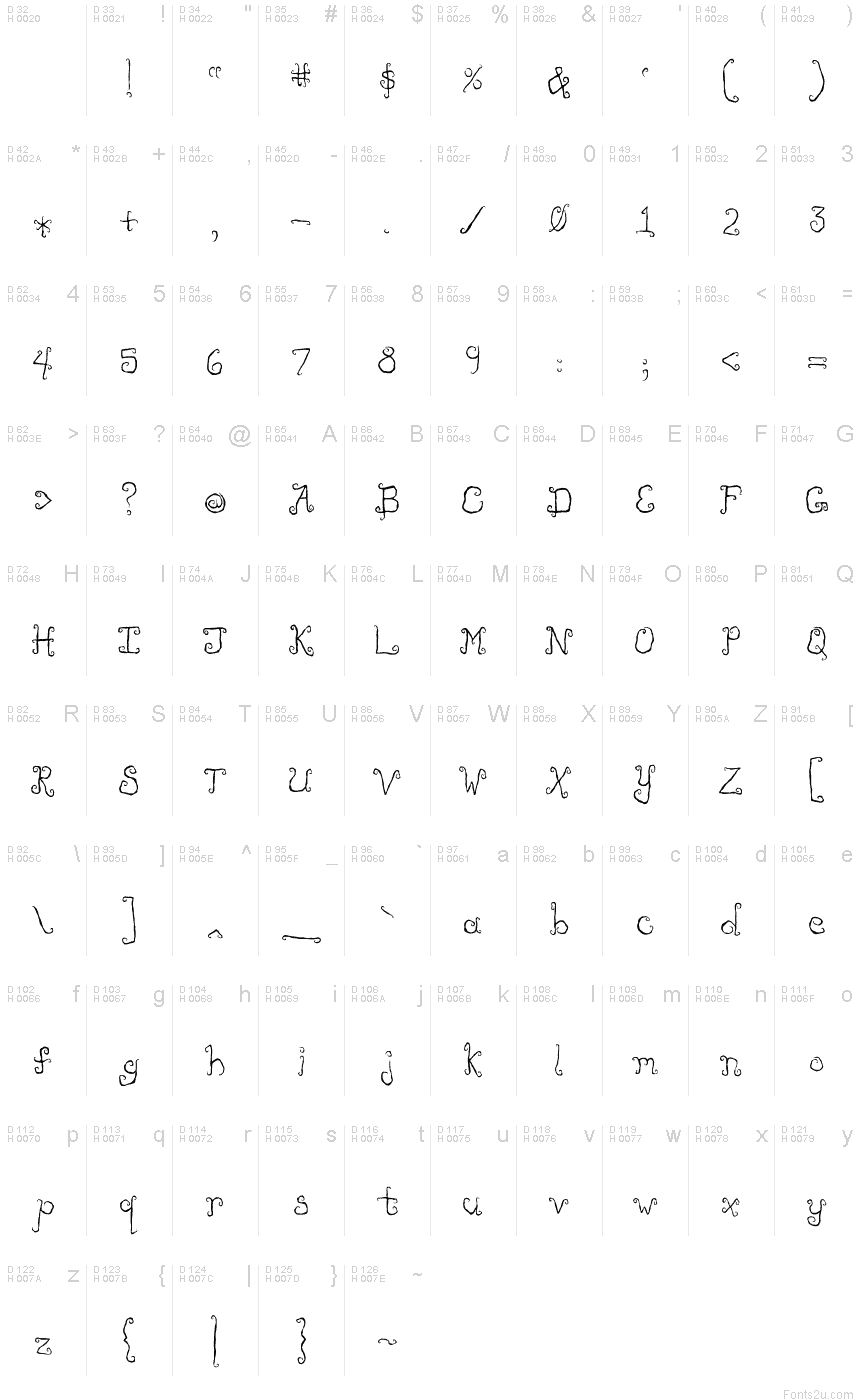
Like Cockatoos Condensed
Like Cockatoos Condensed to darmowy, zakręcony krój typu display autorstwa Kevina Richeya, przypominający odręczne pismo pełne zabawnych pętli i pierzastych detali. Cienkie, drżące kreski i zawinięte końcówki nadają słowom animowany, lekko ekscentryczny charakter, nie stając się przy tym przesadnie ozdobnymi.
Ten bezpłatny font świetnie sprawdzi się na okładkach książek dla dzieci, nietypowych plakatach, w menu kawiarni, na kartkach okolicznościowych i w oryginalnych tytułach. Szczególnie dobrze wygląda w krótkich nagłówkach i przy większych rozmiarach, gdzie wysokie pętle i zwarty rytm mają wystarczająco dużo miejsca, by w pełni zaprezentować swój urok.